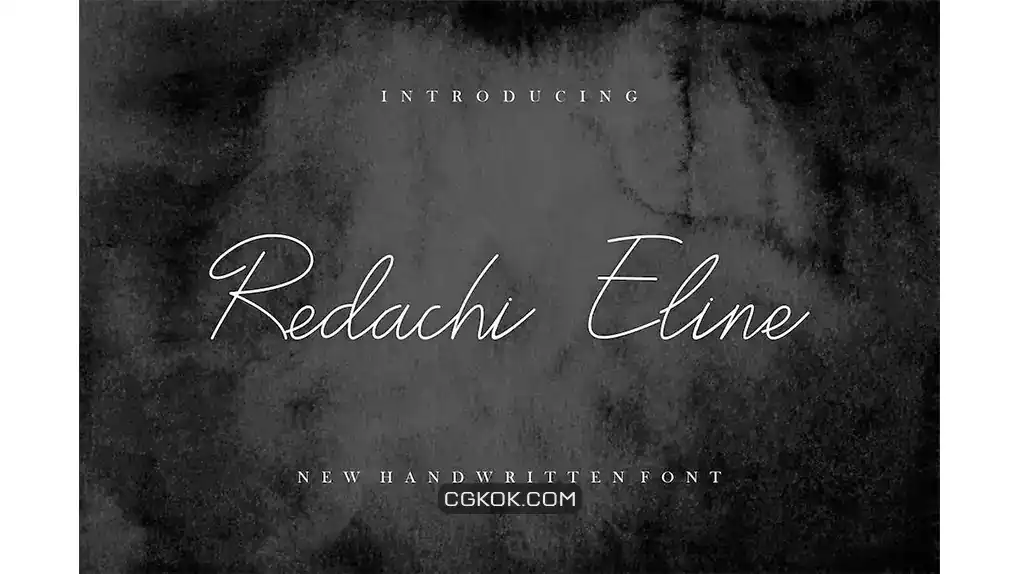
فونت انگلیسی Redachi eline font : این مجموعه شامل یک فونت دست نویس است که برای لوگو، امضا، برندینگ، کارت عروسی، نقل قول‌ های تایپوگرافی، جلد مجله یا کتاب، سربرگ وب‌ سایت، لباس، طراحی بسته‌ بندی و غیره مناسب میباشد.
• فضا بین حروف: معمولی، متراکم
فونت انگلیسی دست نویس